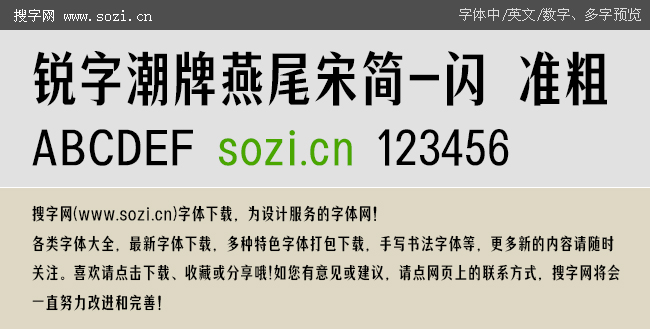
銳字潮牌燕尾宋簡-閃 準粗
搜字網提供一款銳字潮牌燕尾宋簡-閃 準粗中文字體下載,銳字潮牌燕尾宋簡-閃是一款非典型宋體字,它簡化了部分宋體字特征,橫豎筆形粗細視覺相等,整體比例拉長,字形看上去挺拔、俊秀、優雅,字體內部空間松緊度均勻,合理的留白安排給人以視覺上的輕松感受,精致而透氣。從而呈現出一種更加簡約、更具現代感的宋體字。用于標題設計、海報設計、包裝設計等場景廣泛應用。(本字體為個人非商用版,商用請聯系作者購買授權)